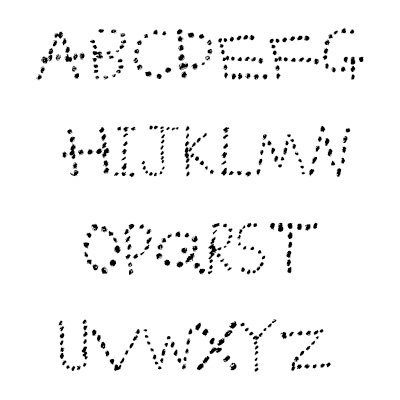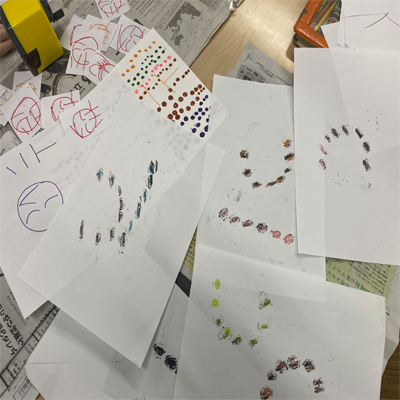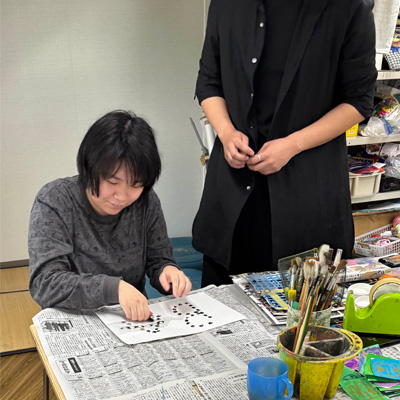
ドットレター
ひとつぶずつ、ことばになる。
ArtistHIROMIX
DesignerLOU
Organizationむつみ工房
集中して取り組めました。頑張ったので是非皆さんに使ってほしいです。(HIROMIX)
赤と青の小さなドットで描いた、落書き風のアルファベット。手描きのゆるさと色のリズムが、文字に遊び心を加えます。(LOU)
一つ一つ手書きのドットの力強さを感じる作品です。ポップで楽しい気分になれます。(むつみ工房)